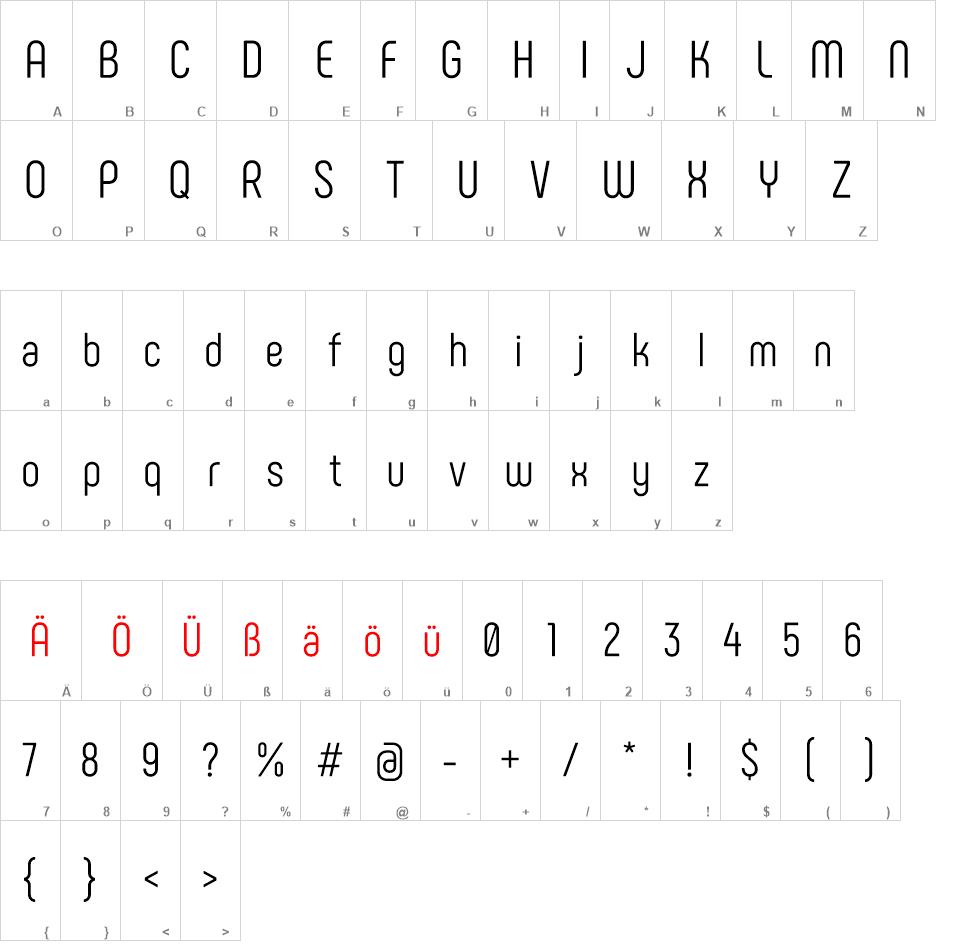
Phenomena
Phenomena font
Phenomena ist eine moderne Sans-Schrift mit Serifenschrift basierend auf runden geometrischen Formen. Phänomene Familie.
Diese Preise sind leicht und retro. Abgerundete Ecken mildern die allgemeine Wahrnehmung und ergänzen die geometrische Ästhetik der Familie.
Die Ereignisse umfassen mehr als 500 Zeichen in einer Vielzahl von Sprachen - Unterstützung für lateinische und kyrillische Zeichen sowie erweiterte bulgarische Lokalisierungsfunktionen.
Schriftdesigner Radomir Tinkov und Plamen Motev.